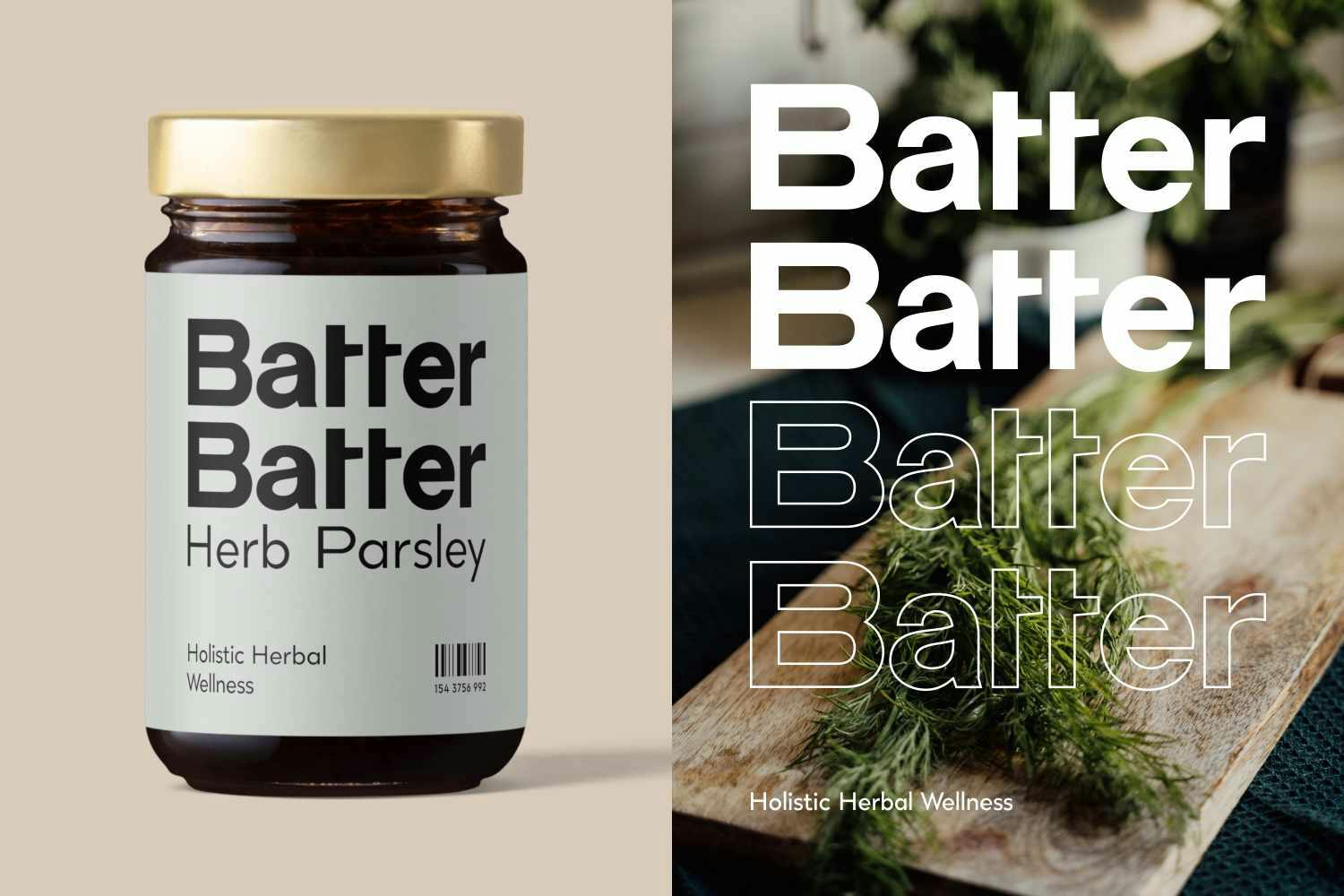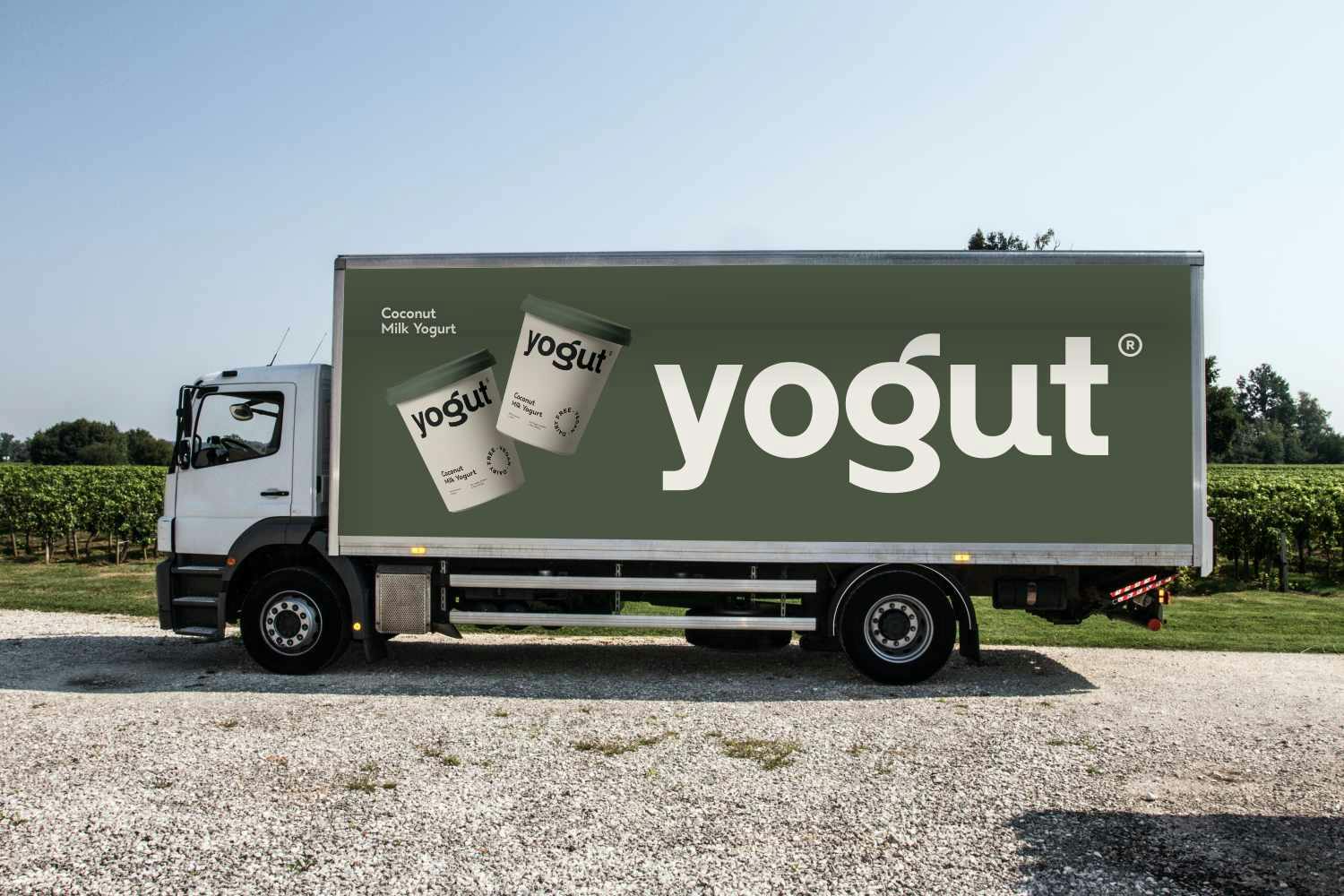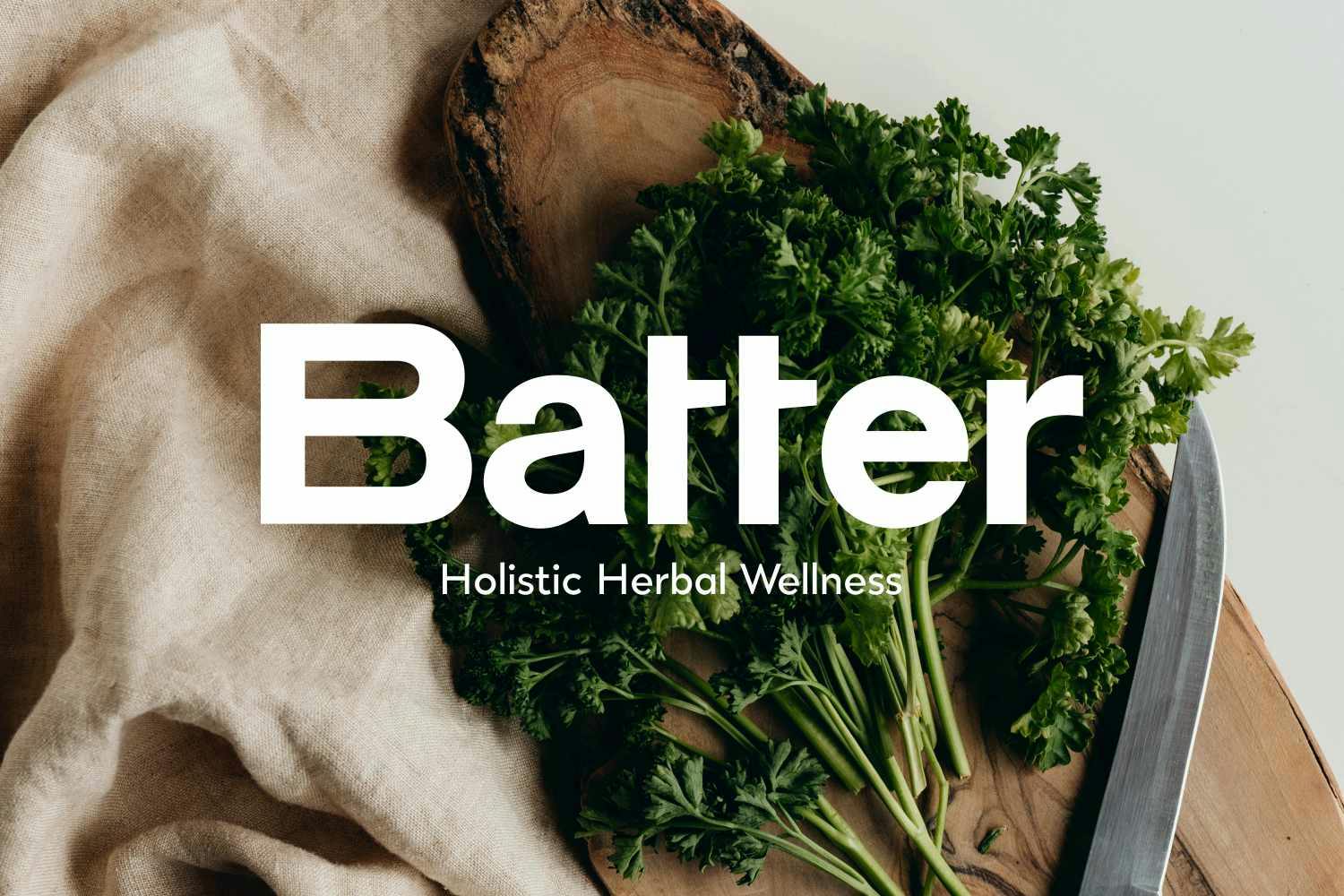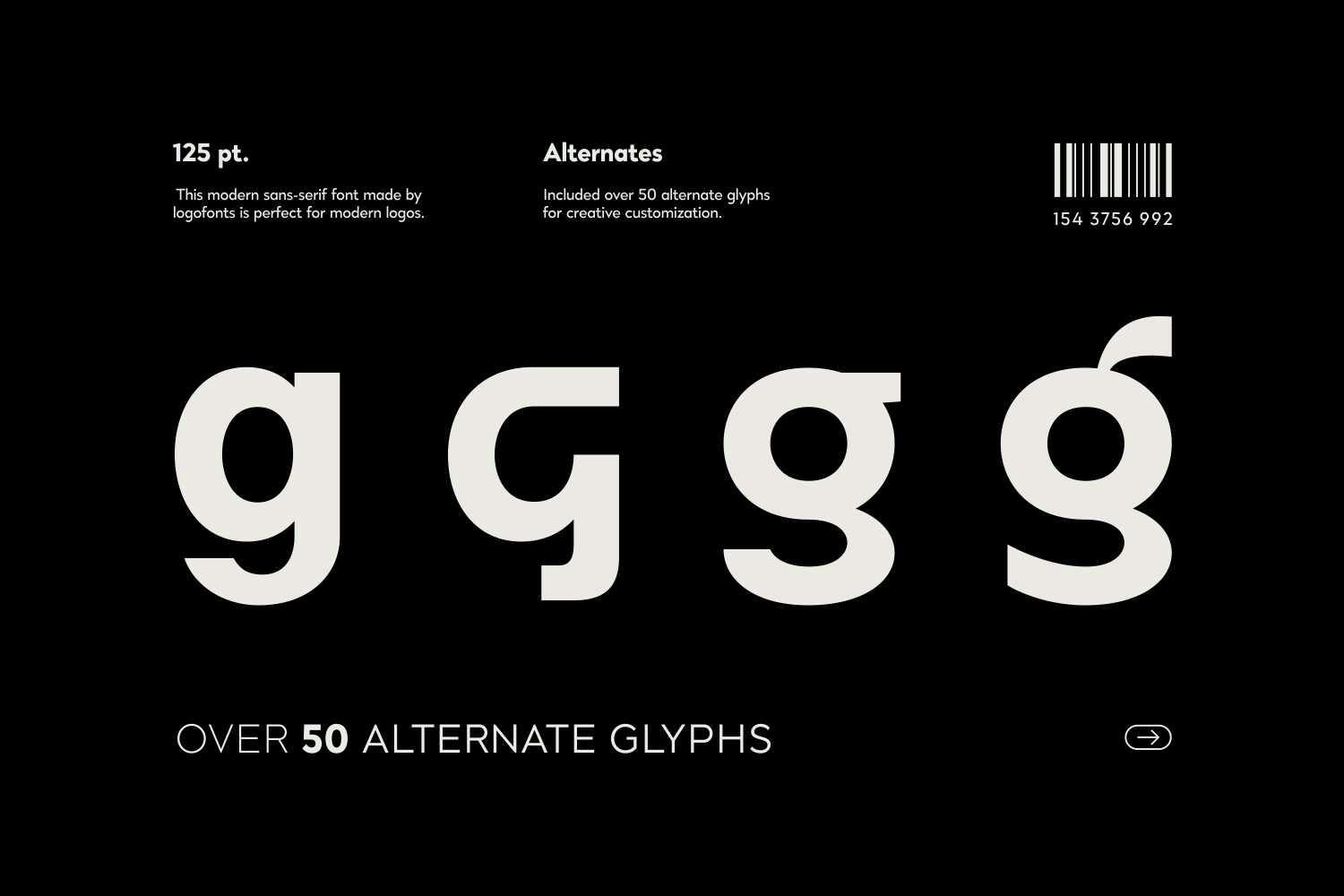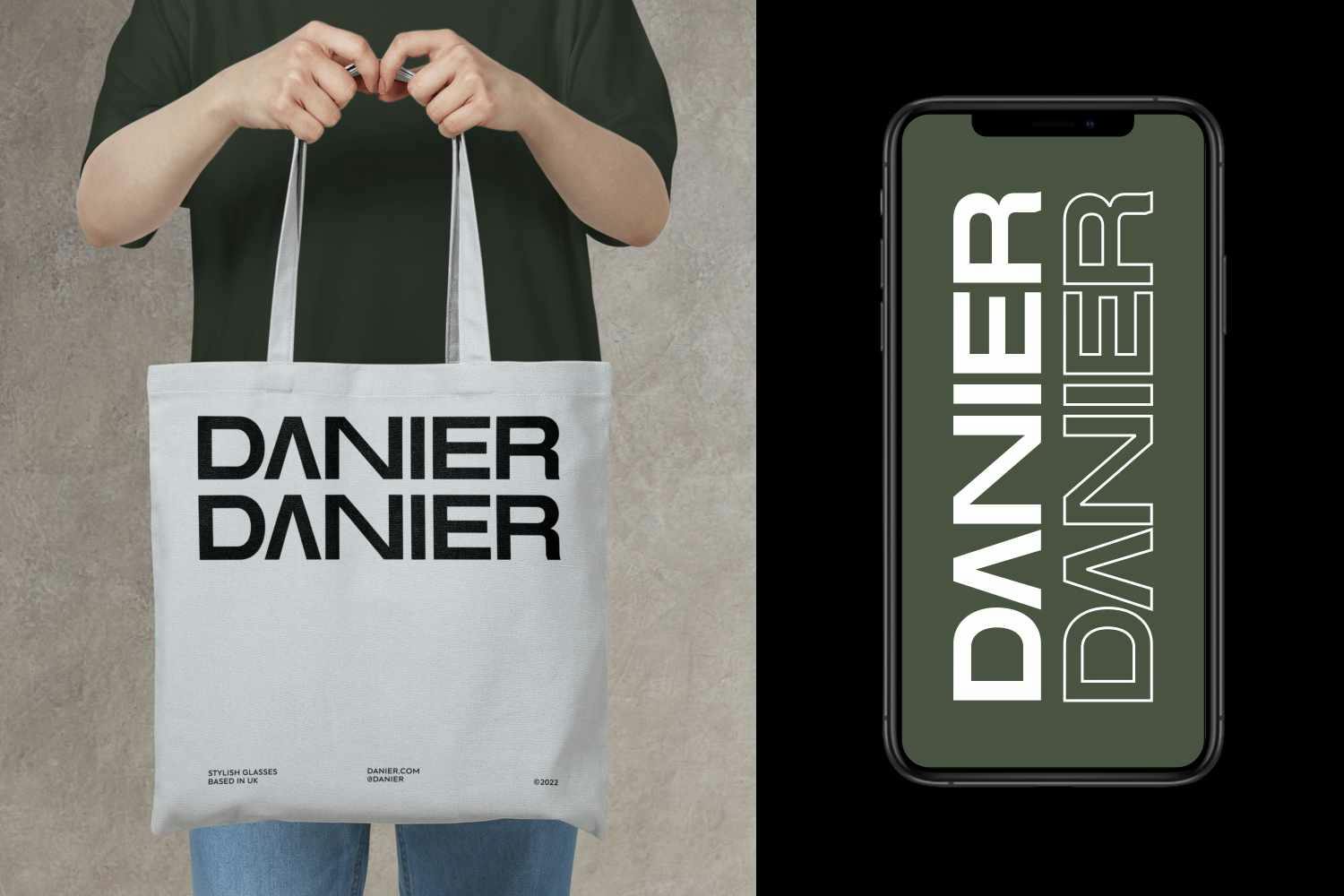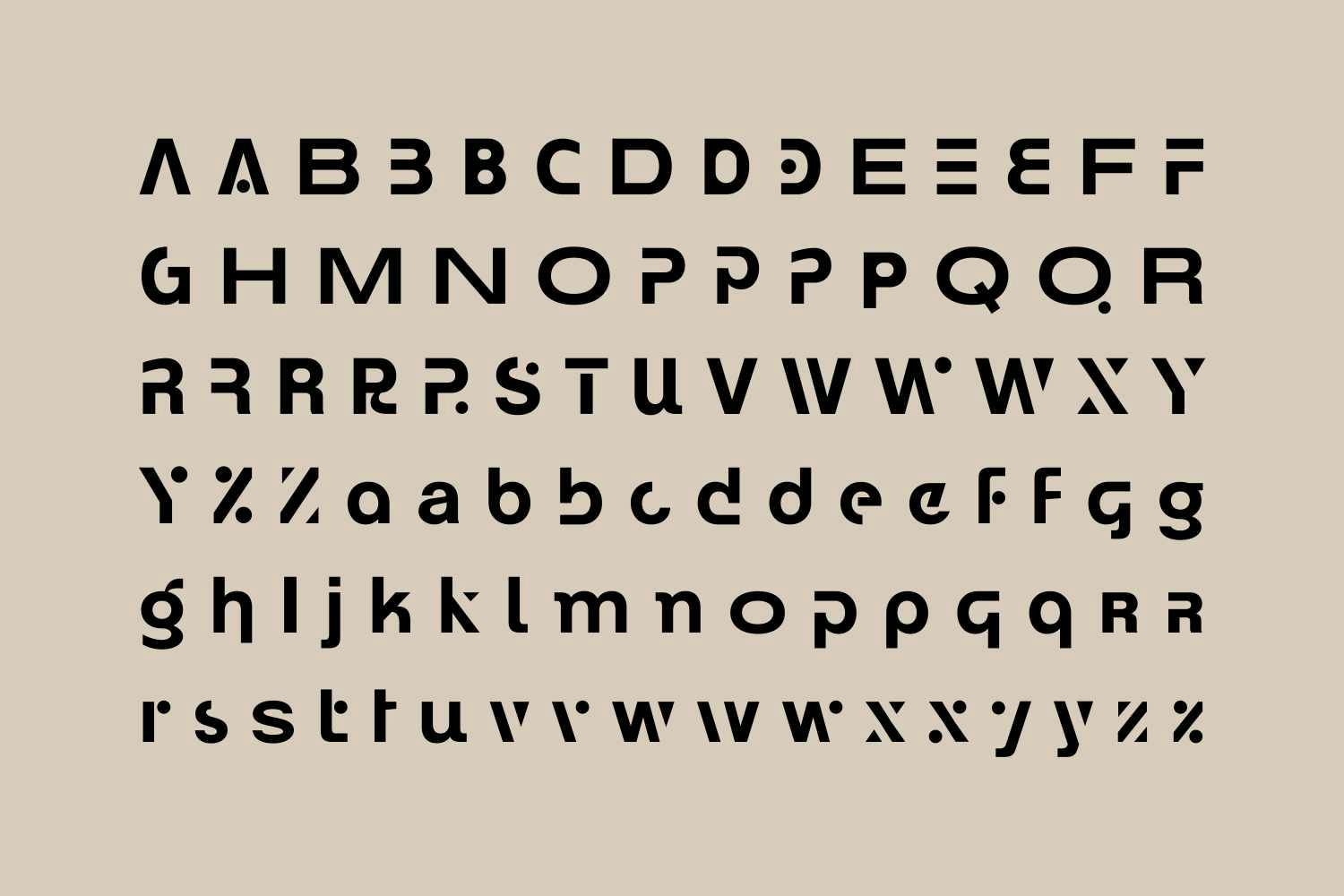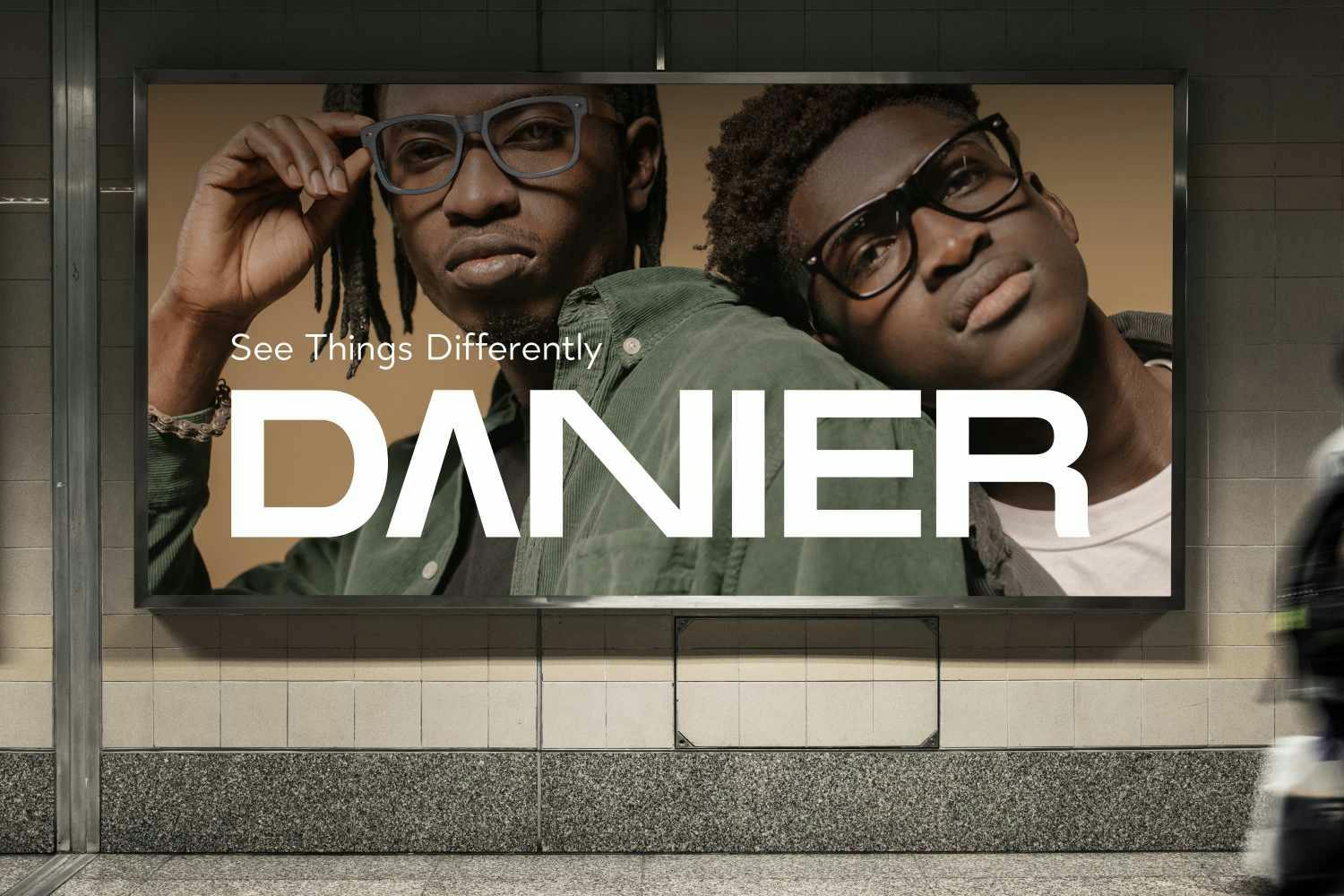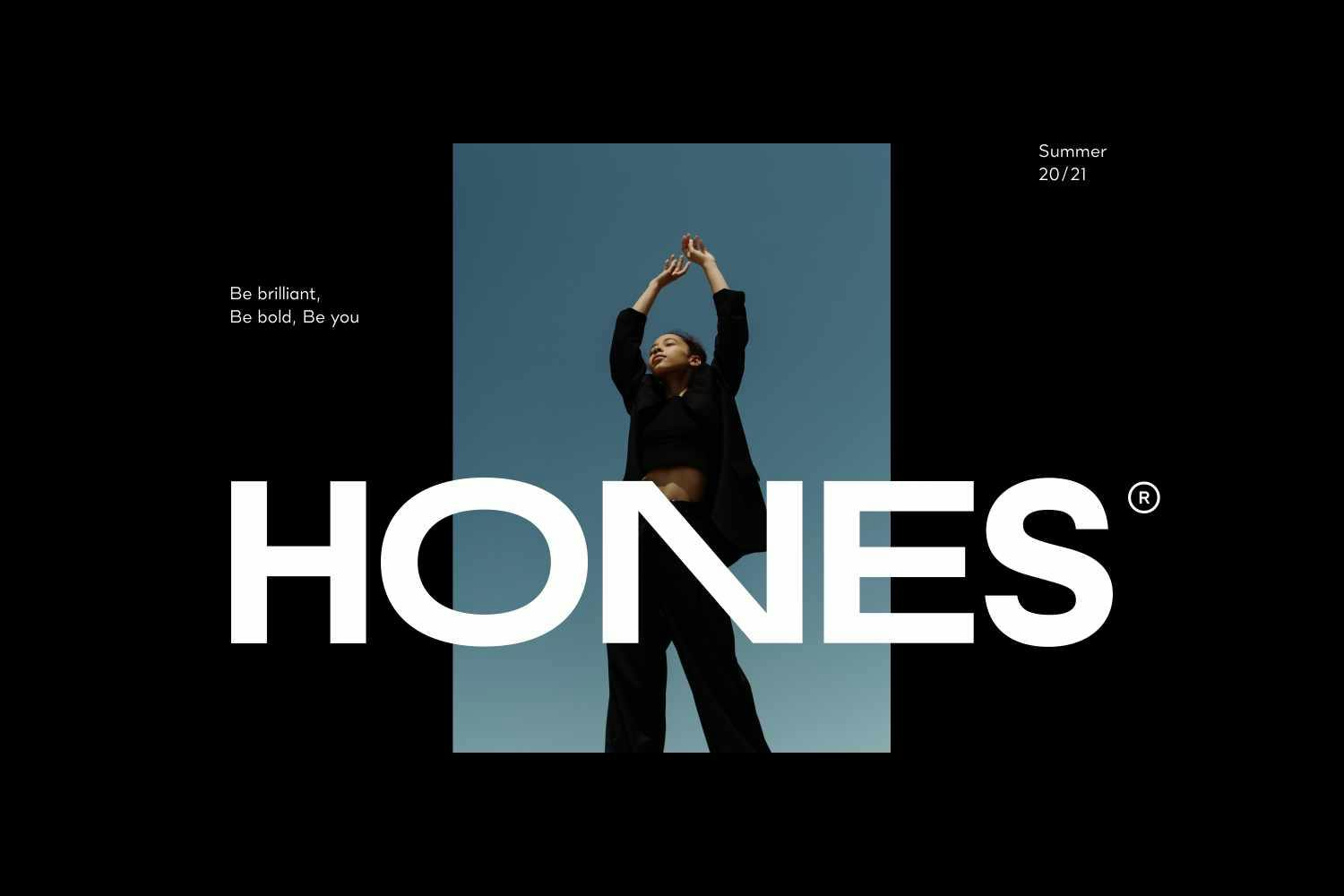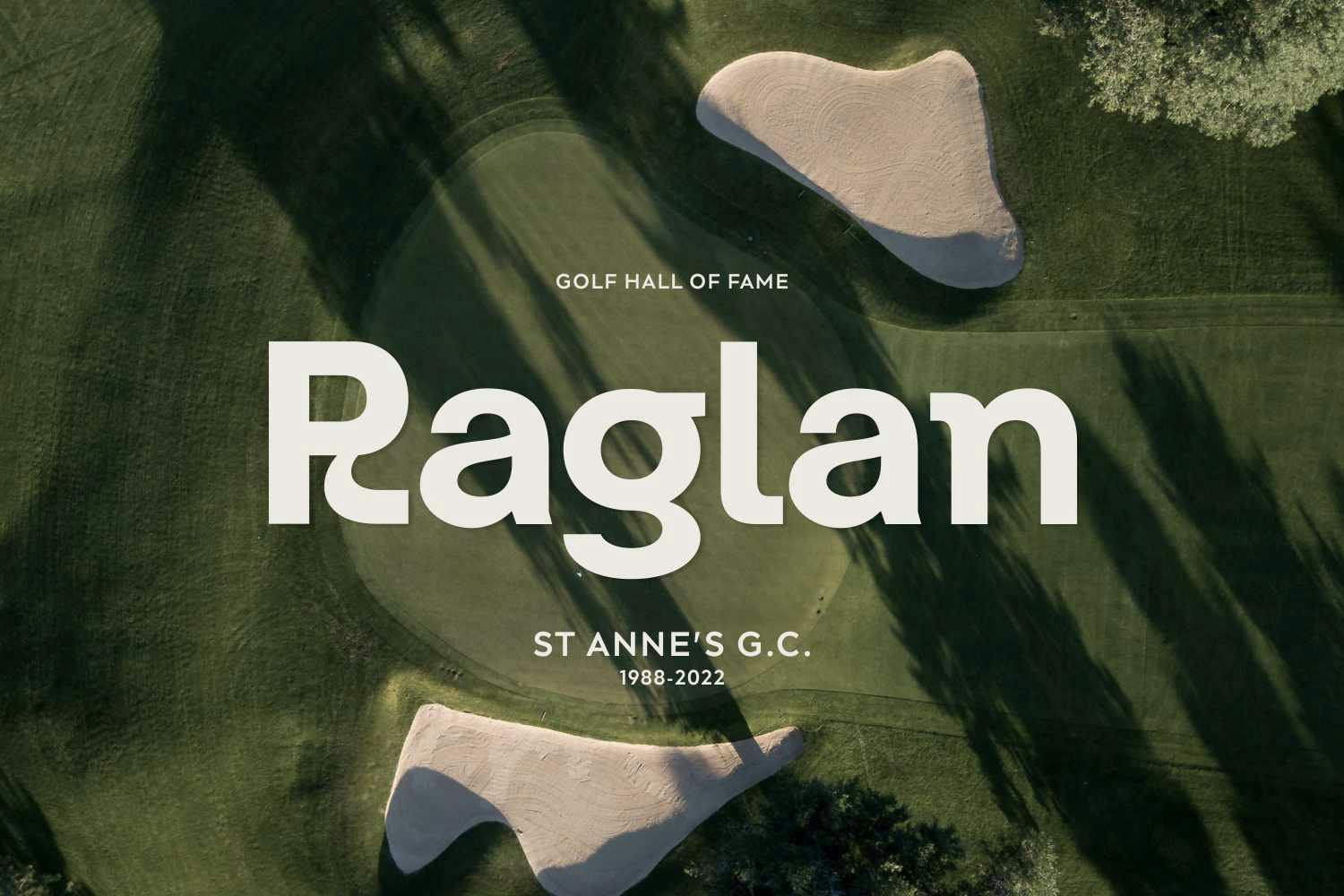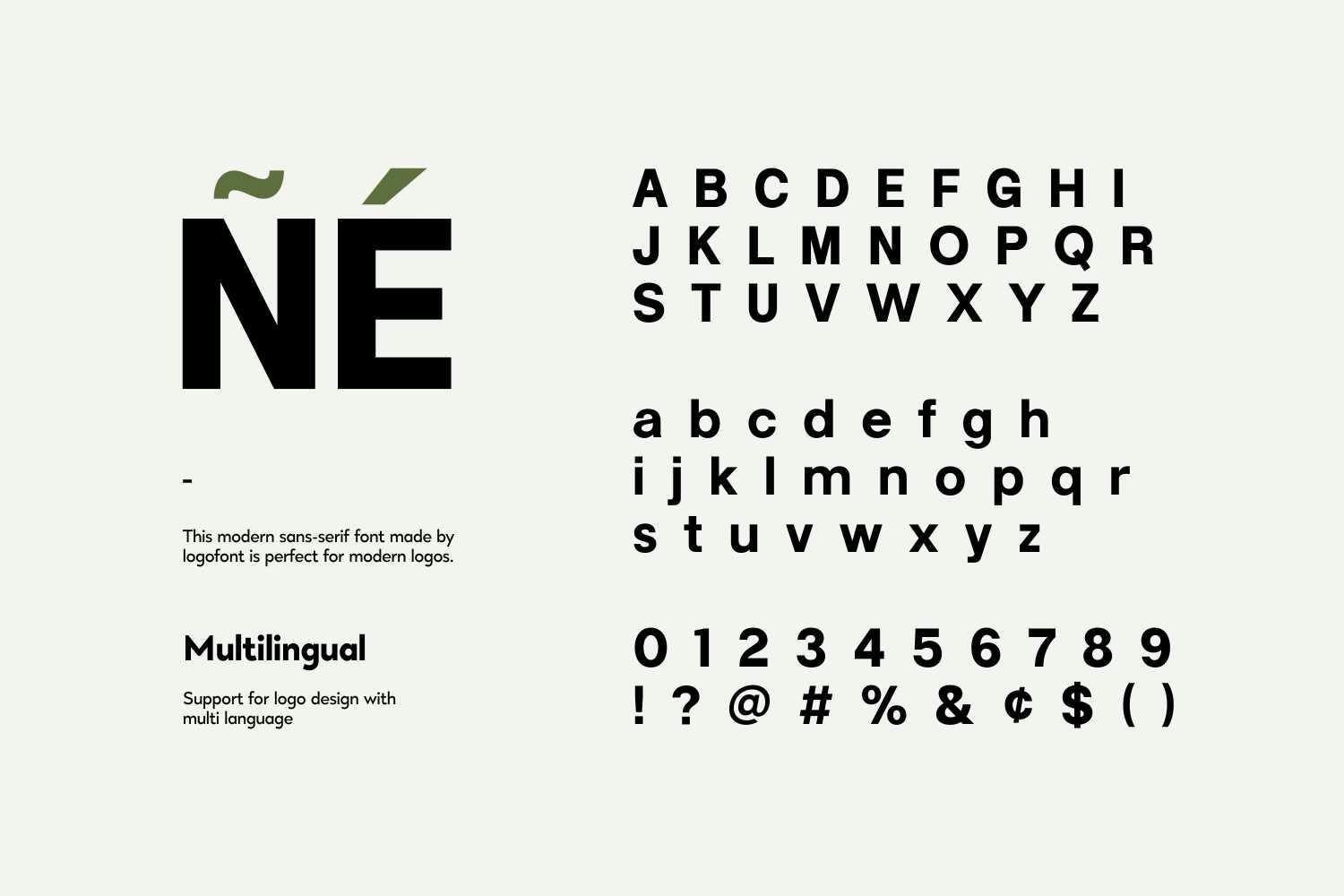
فونت Helotypo از نوع Sans Serif است که برای طراحی لوگو محصولات، پوسترها، عناوین، لوگو کارت، وبسایتها، مجلات، بستهبندی، لوازمالتحریر و بسیاری موارد دیگر بسیار مناسب است. با استفاده از این فونت، میتوانید بهراحتی نوع لوگوی خود را ایجاد کنید. فونت Helotypo دارای ویژگی Open Type است که به شما امکان دسترسی به مجموعهای بزرگ از حروف جایگزین و بسیاری از ligatureها را میدهد تا کار طراحی برای شما آسانتر شود.